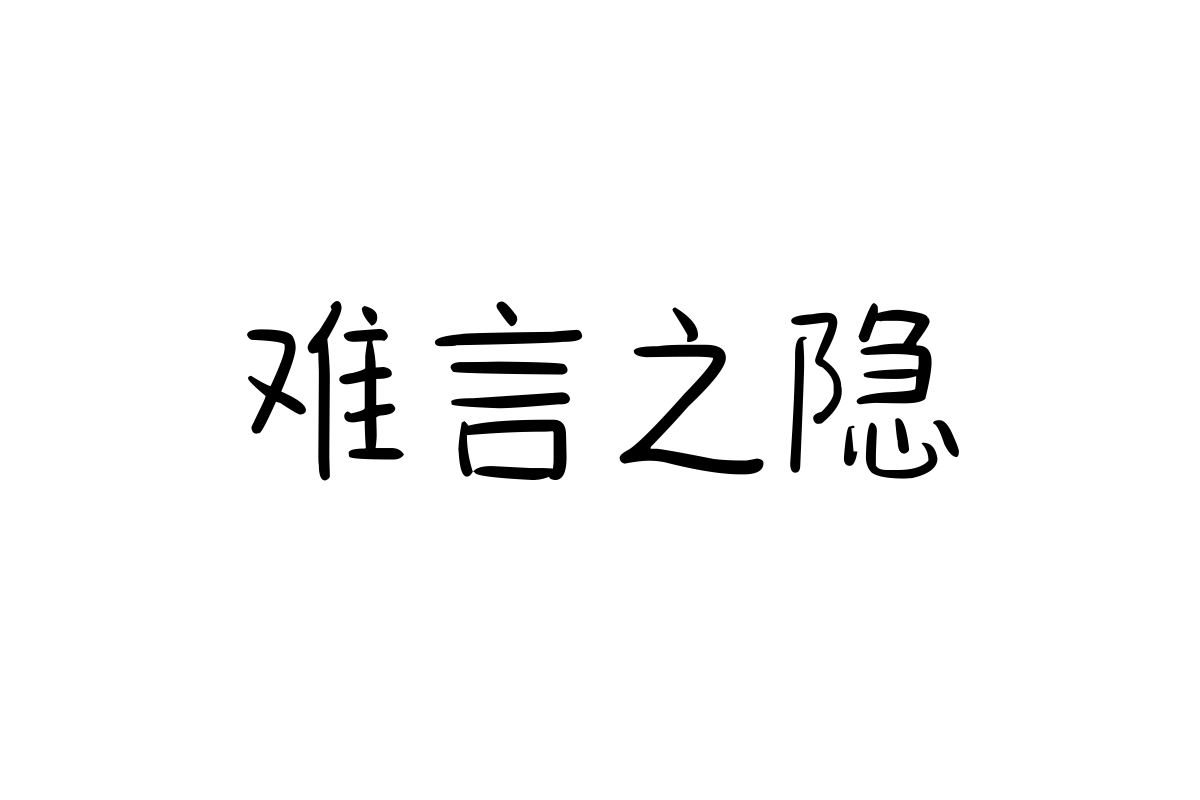
汉仪新蒂花园体是一款具有现代感和艺术气息的中文字体。它采用了独特的字形设计和排版风格,使得文字在视觉上更加美观、大方。这款字体适用于各种商业、广告、设计等领域,能够为作品增添一份独特的魅力。
汉仪新蒂花园体的特点包括:
1. 字形设计独特:该字体采用了现代的字形设计,线条流畅、简洁,给人一种清新、时尚的感觉。同时,字体的大小和间距也经过精心设计,使得文字在页面上呈现出良好的视觉效果。
2. 排版风格多样:汉仪新蒂花园体支持多种排版方式,包括常规、斜体、粗体等,能够满足不同场景的需求。无论是用于标题、正文还是装饰元素,都能够展现出其独特的魅力。
3. 适用范围广泛:这款字体适用于各种商业、广告、设计等领域,能够满足不同行业的需求。无论是企业宣传、产品包装还是网页设计,都能够为其增添一份独特的魅力。
总之,汉仪新蒂花园体是一款具有现代感和艺术气息的中文字体,适用于各种商业、广告、设计等领域。它的独特字形设计和排版风格使其在视觉上更具吸引力,能够为作品增添一份独特的魅力。